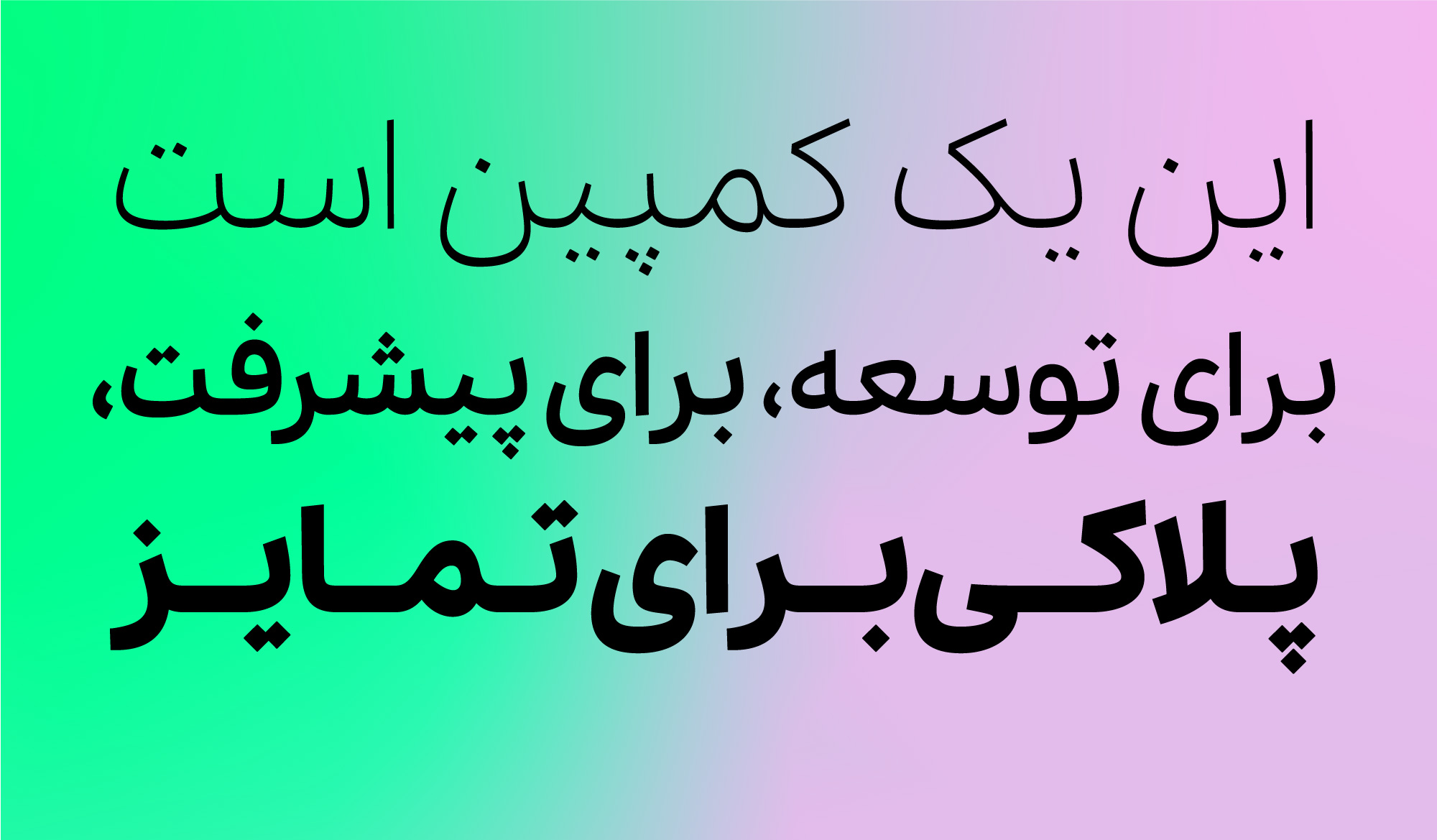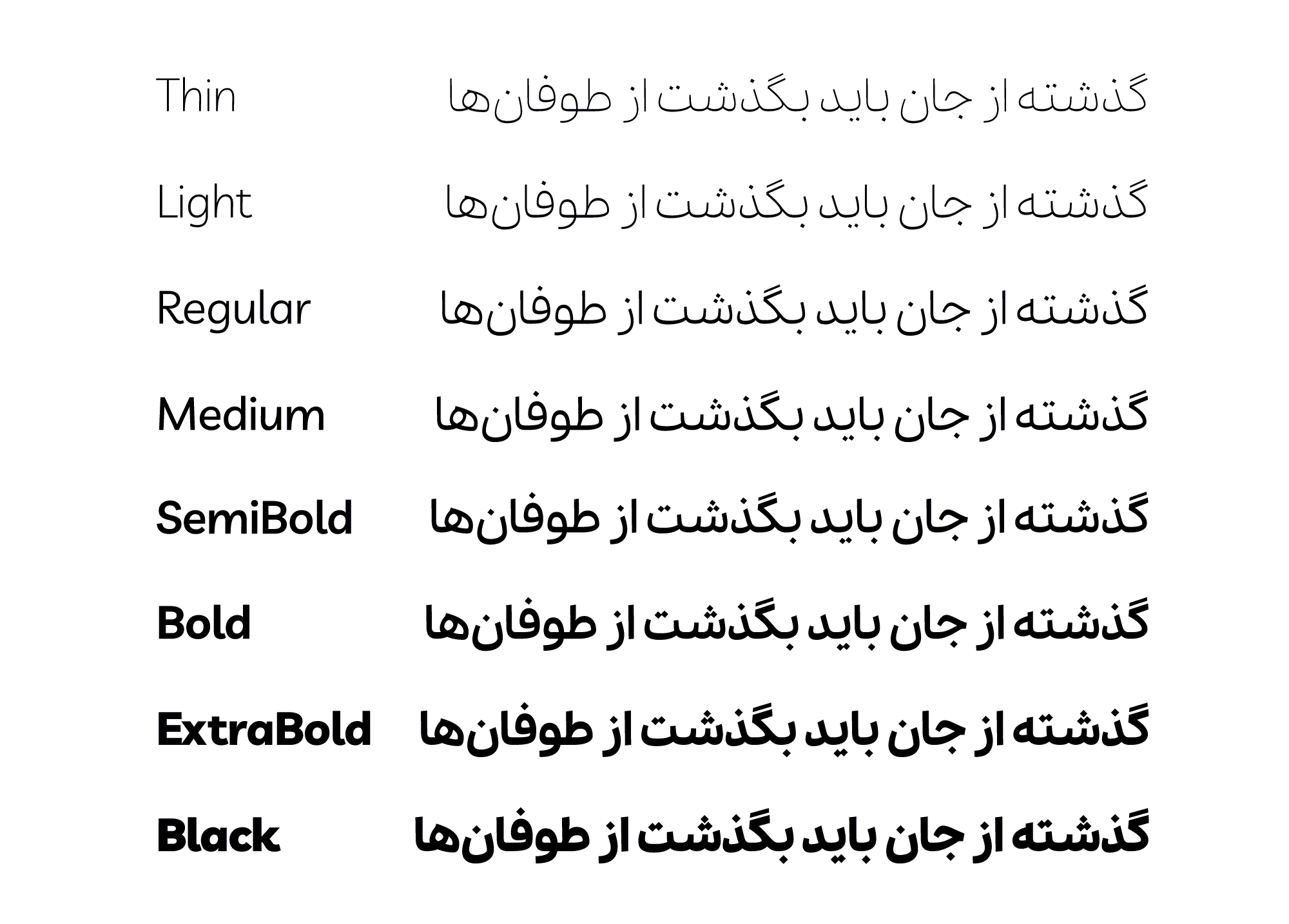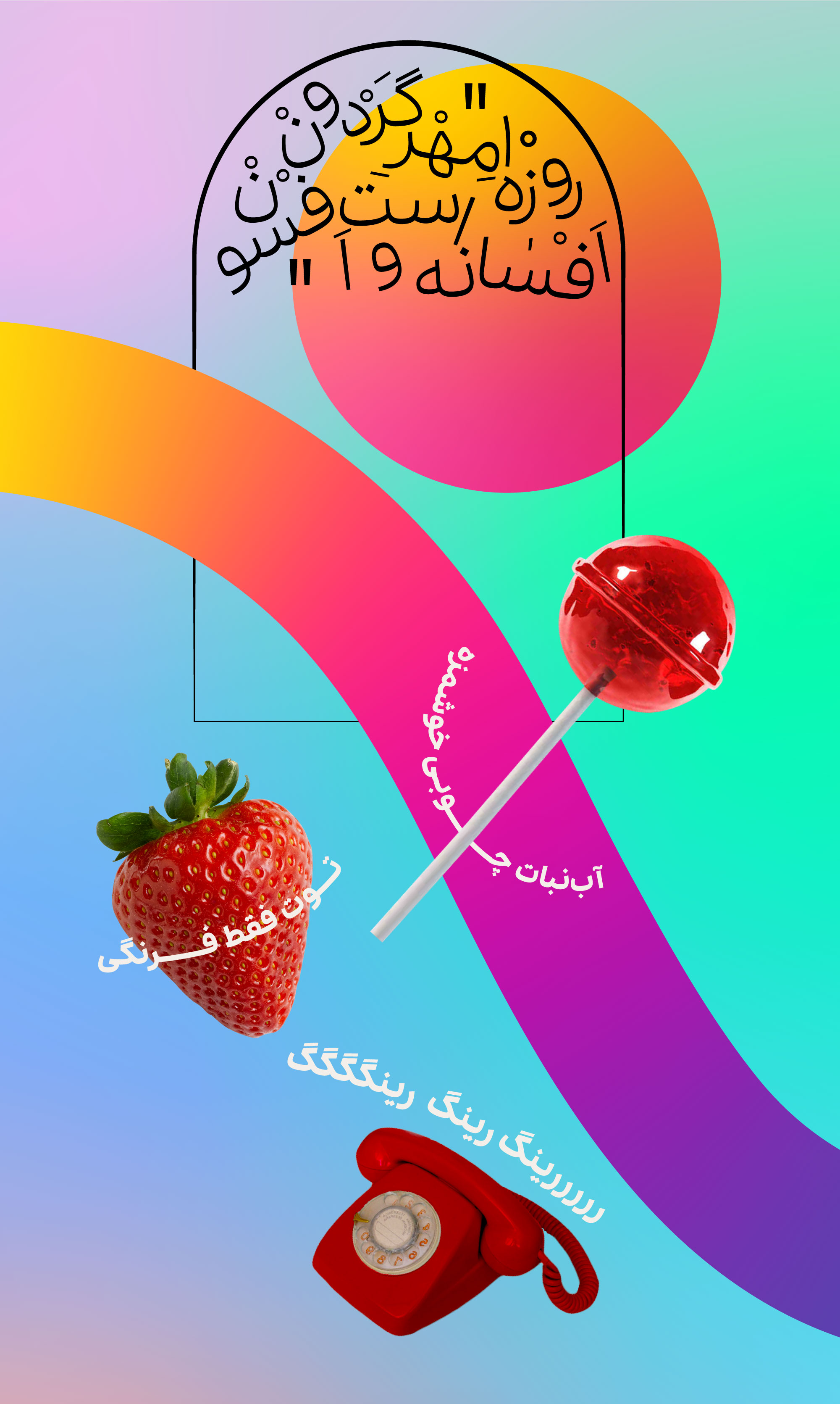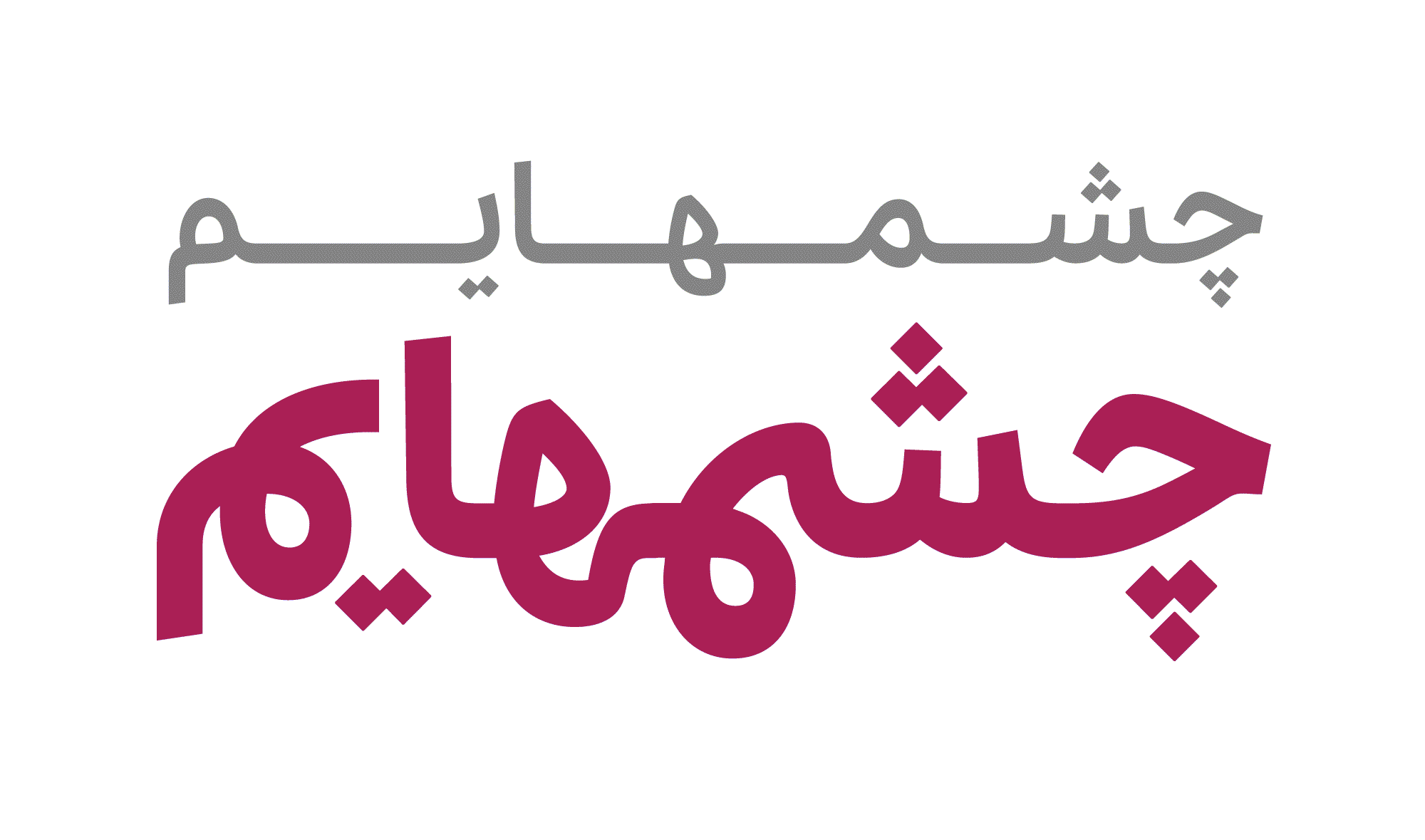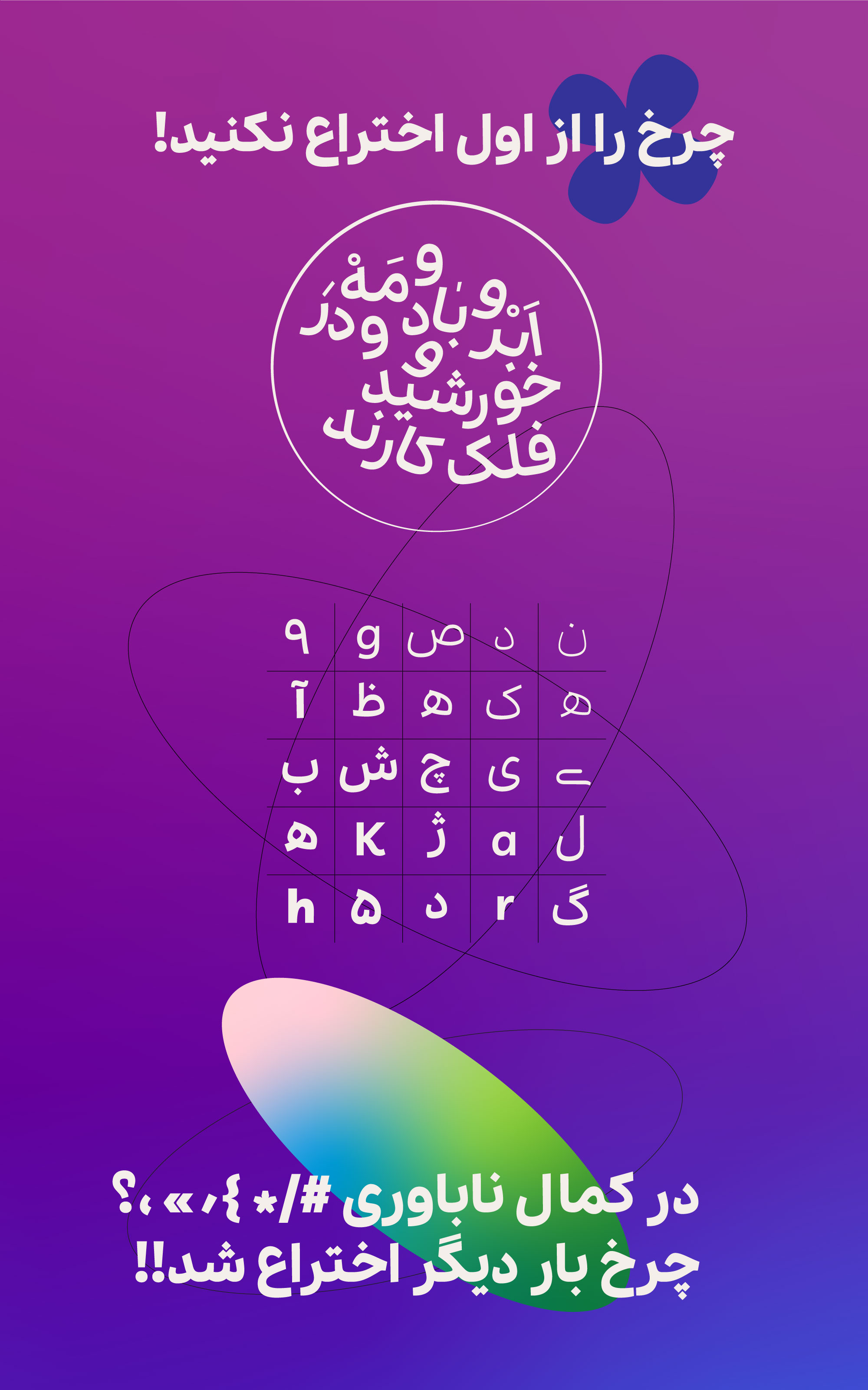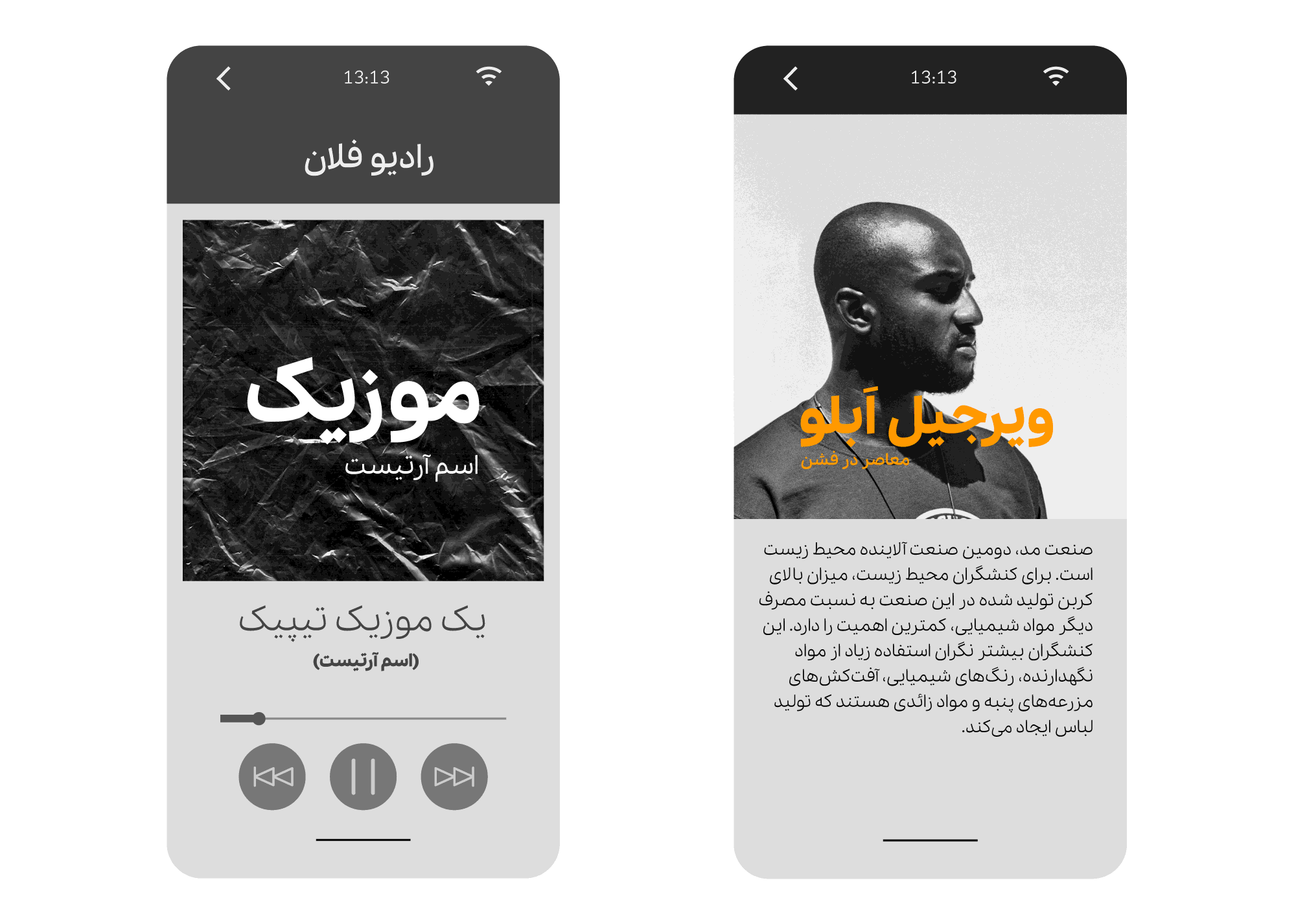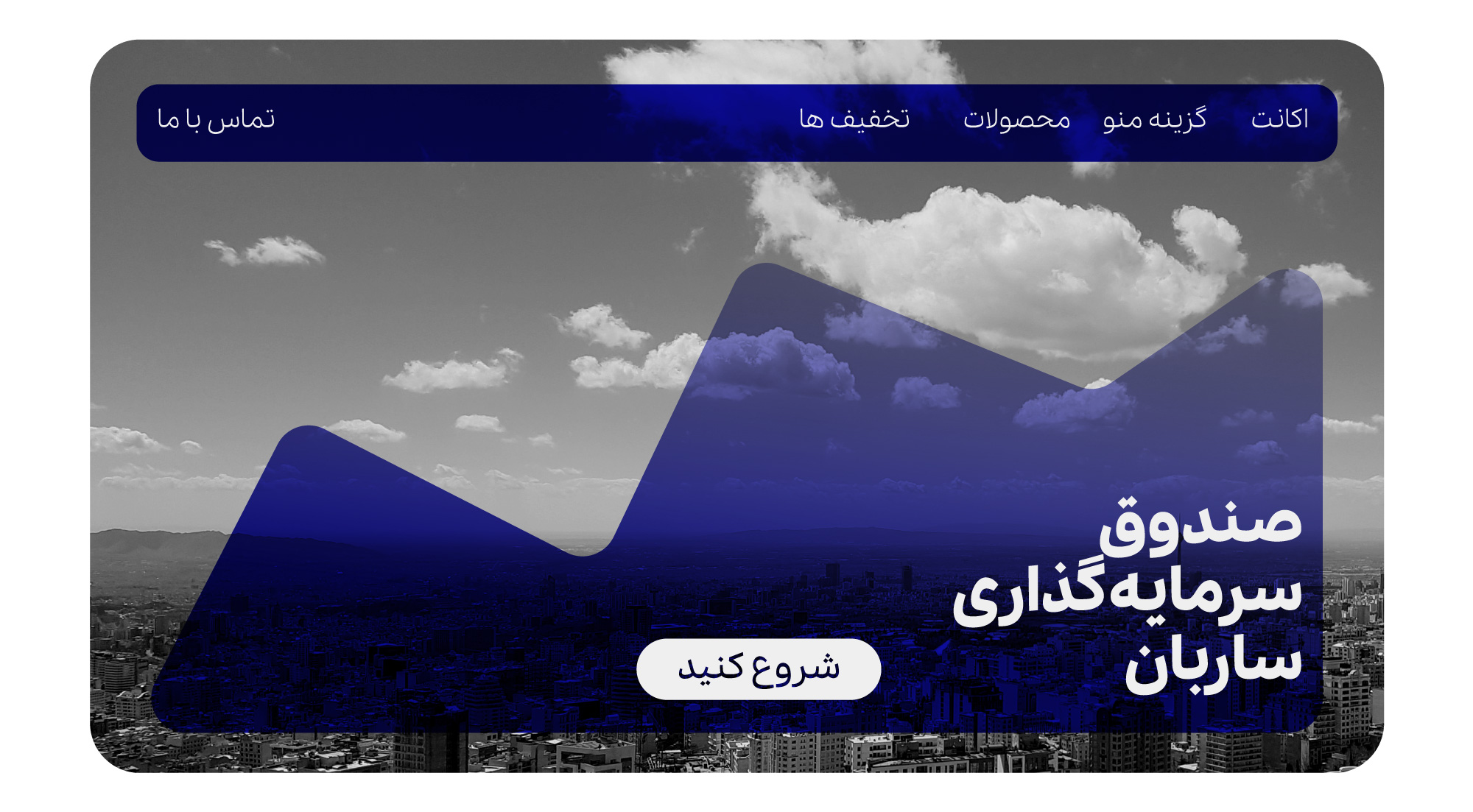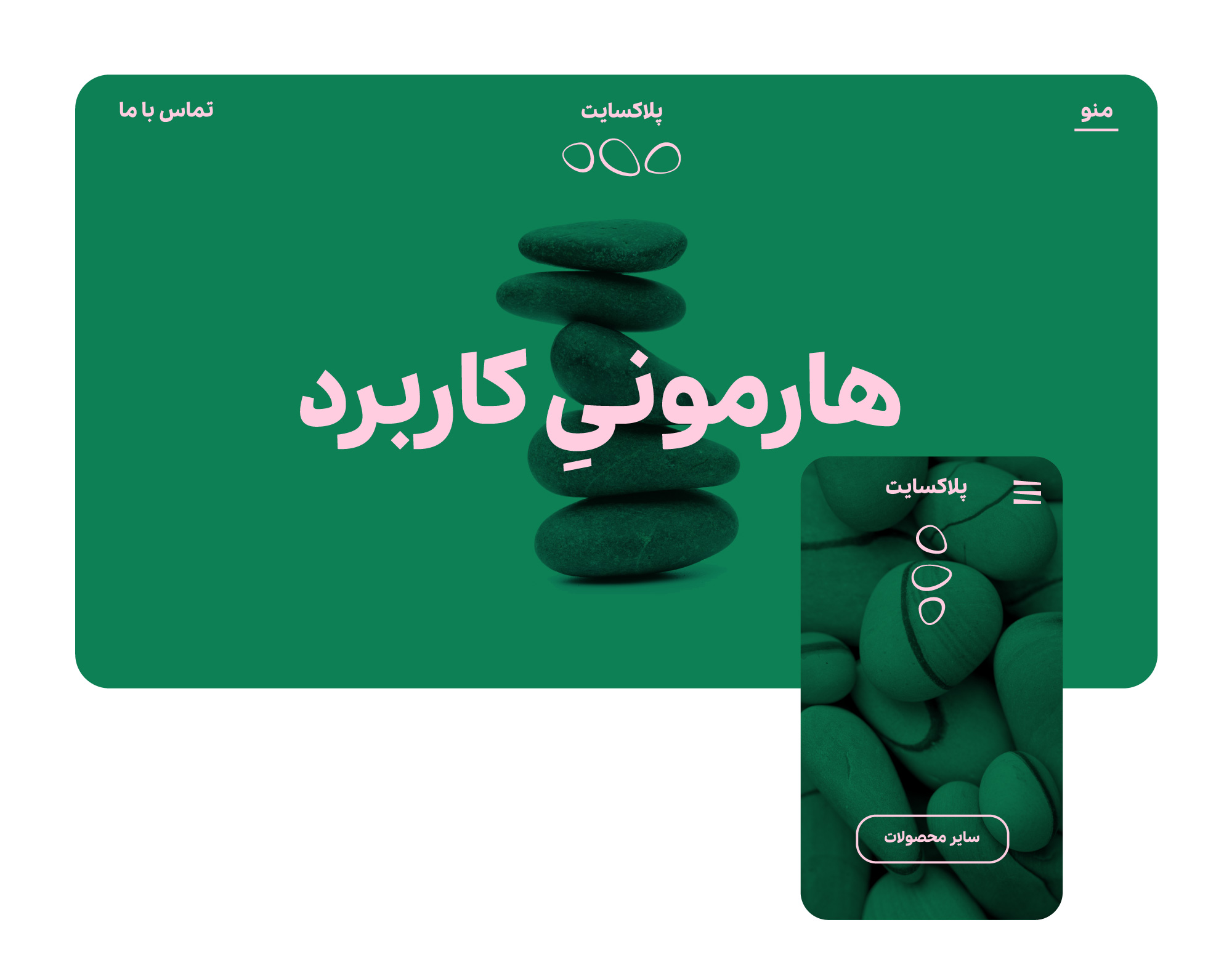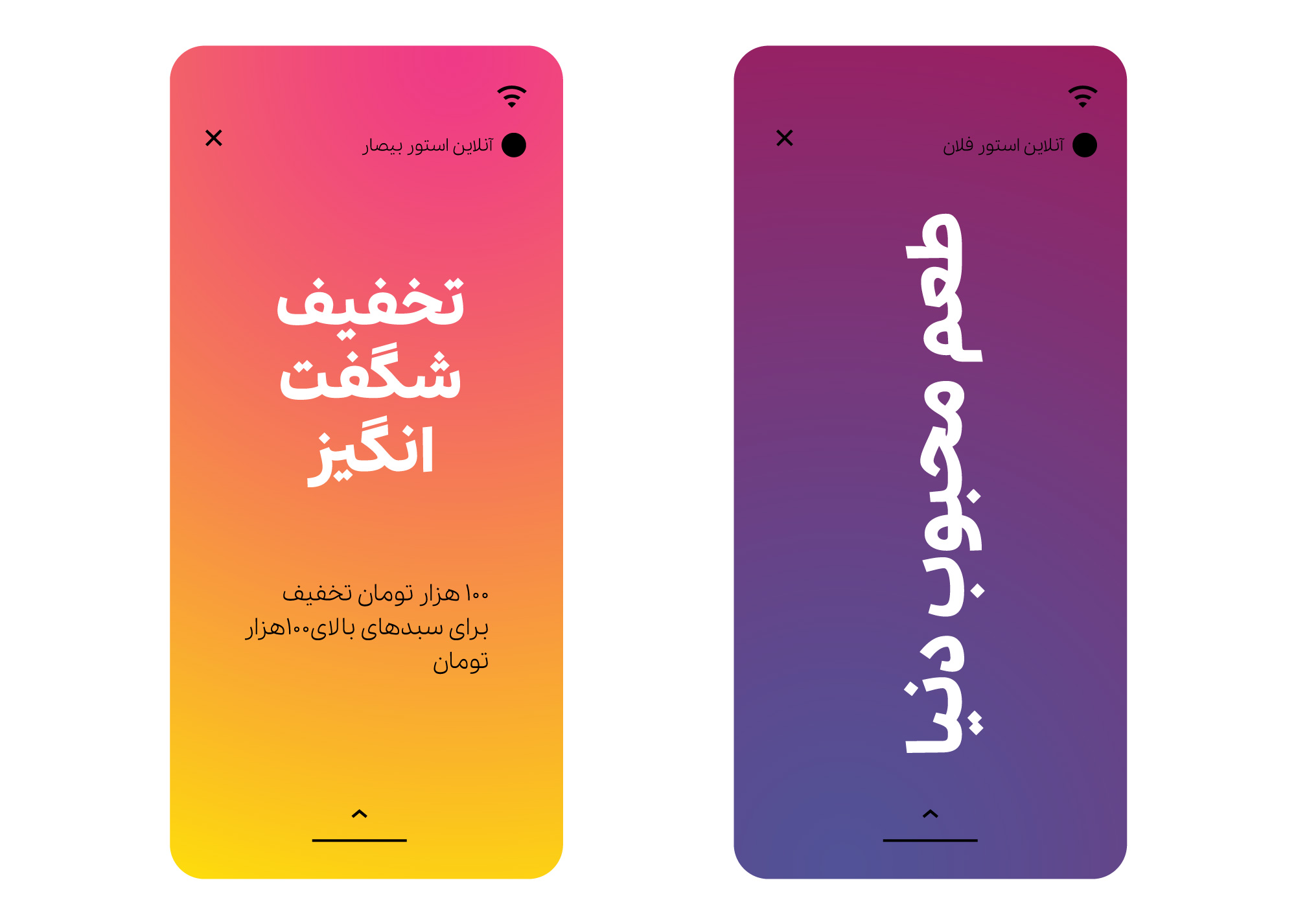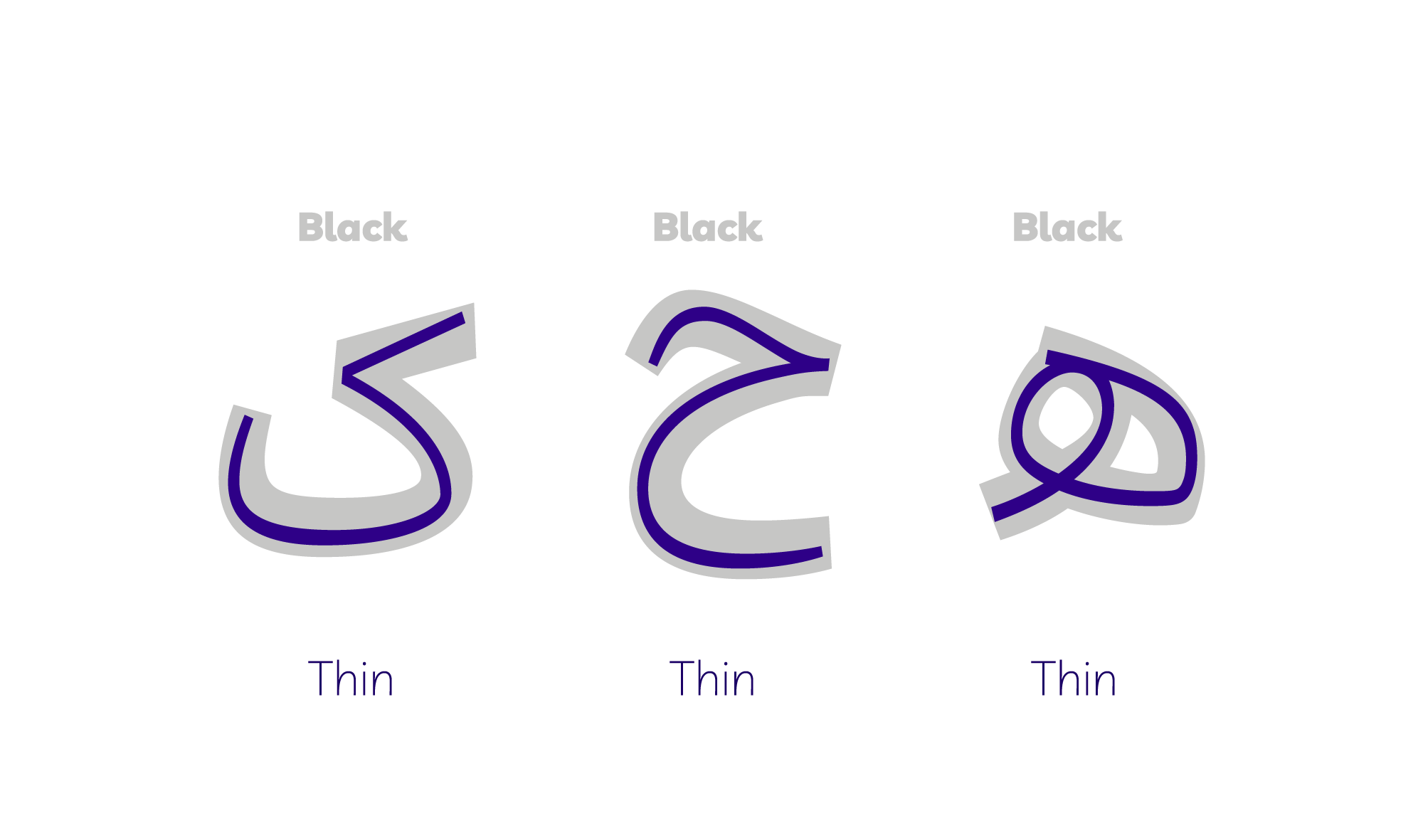
فونت پلاک از زبانهای فارسی، عربی و انگلیسی پشتیبانی میکند.
تنوع وزنها
خانواده فونت پلاک در هشت وزن Thin, Light, Regular,Medium,SemiBold, Bold, ExtraBold, Black طراحی شده است. همه وزنها فونت شامل کاراکتر های لاتین هستند و میتوان متن را در هر سه زبان انگلیسی فارسی و عربی تنظیم کرد. فونت پلاک طبق استاندارد های جهانی ساخته شده و در تمامی محیط های متنی و نرمافزاری که از خط فارسی پشتیبانی میکنند قابل استفاده است.
ترکیبات اختیاری
در فونت پلاک تعداد زیاد ترکیب اختیاری نیز وجود دارد که دست طراحان را برای استفادهی متنوع و خلاقانه تر از این تایپفیس باز میگذارد. شما میتوانید به صورت دستی این ترکیبات اختیاری را در نرمافزار های مخصوص طراحی گرافیک و … فعال کنید.
هدف از طراحی فونت پلاک، رسیدن به خاکستری مناسب و قابل استفاده در محیط وب و اپلیکیشن های فارسی بوده است.
با این وجود به طراحی جداگانه ی حروف نیز اهمیت زیادی داده شده است تا در کنار کاربرد، فونت پلاک، زیبایی قابل قبولی را به طراح ارائه دهد.
طراحی وزن های فونت پلاک به گونه ای صورت گرفته است تا فرم حروف با سنگین تر شدن وزنشان، نمایشی تر شوند. از این رو وزن های بالای فونت پلاک در استفاده ی گرافیکی و تبلیغاتی، علی الخصوص عبارت های کوتاهی نظیر شعار های تبلیغاتی کارآمد خواهد بود.